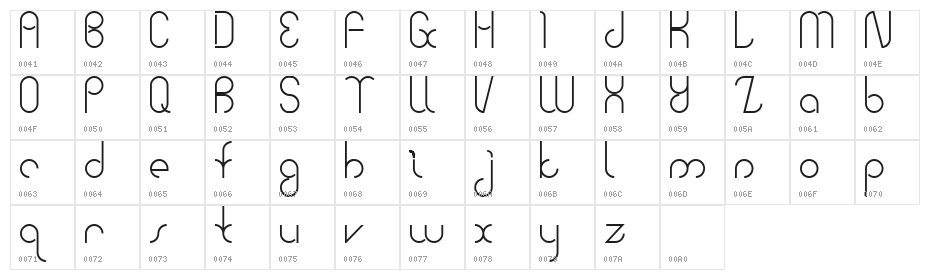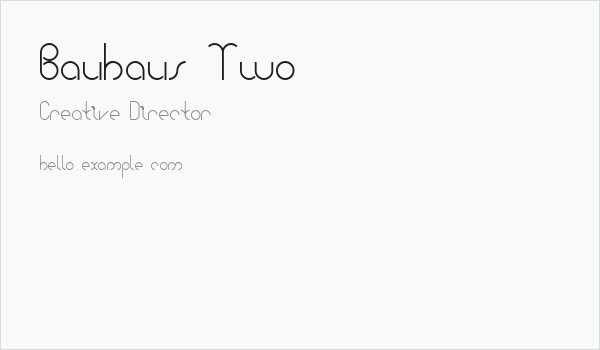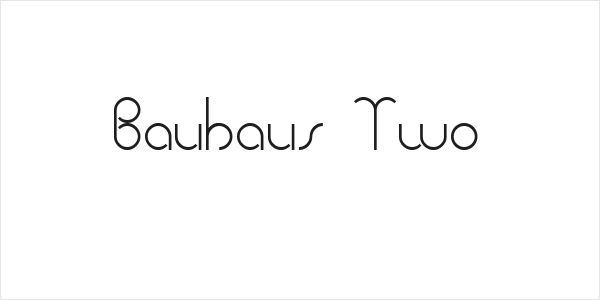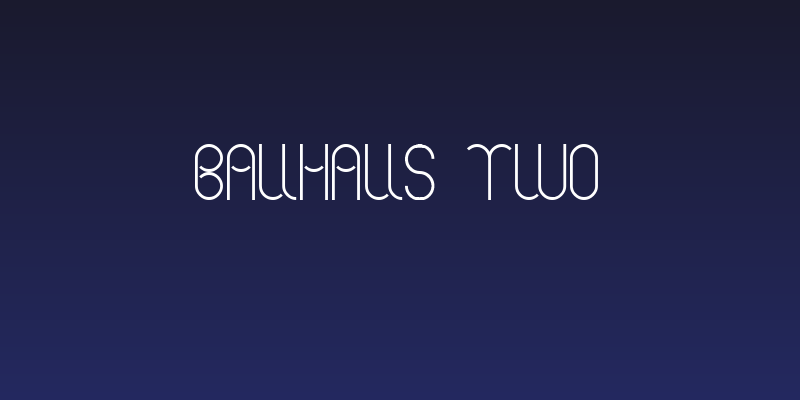
Bauhaus Two Font
| Progetti proposti | Ideal for modern branding, posters, and digital media where a clean, contemporary look is desired. |
Bauhaus Two